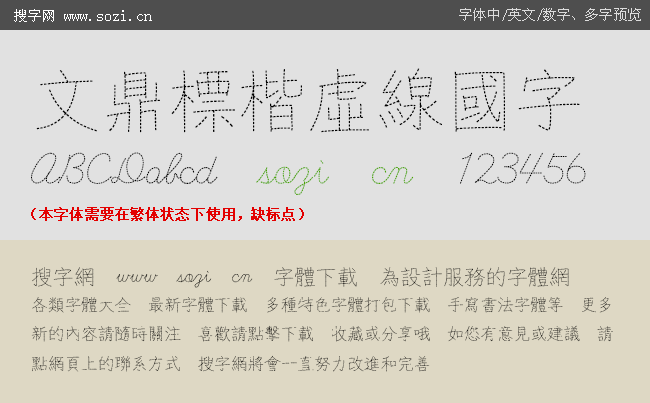
文鼎標(biāo)楷虛線國(guó)字(AR StdKaiGDLB5 Md)
文鼎標(biāo)楷虛線國(guó)字是是搜字網(wǎng)提供一款免費(fèi)中文字體下載。文鼎標(biāo)楷虛線國(guó)字是一款手寫(xiě)化的標(biāo)準(zhǔn)楷書(shū)字體,字體提取自文鼎最新產(chǎn)品“注音小博士3”(Big5編碼),線條做了重繪,十分細(xì)膩,除了摹字外亦可用于各種裝飾。歡迎下載使用。